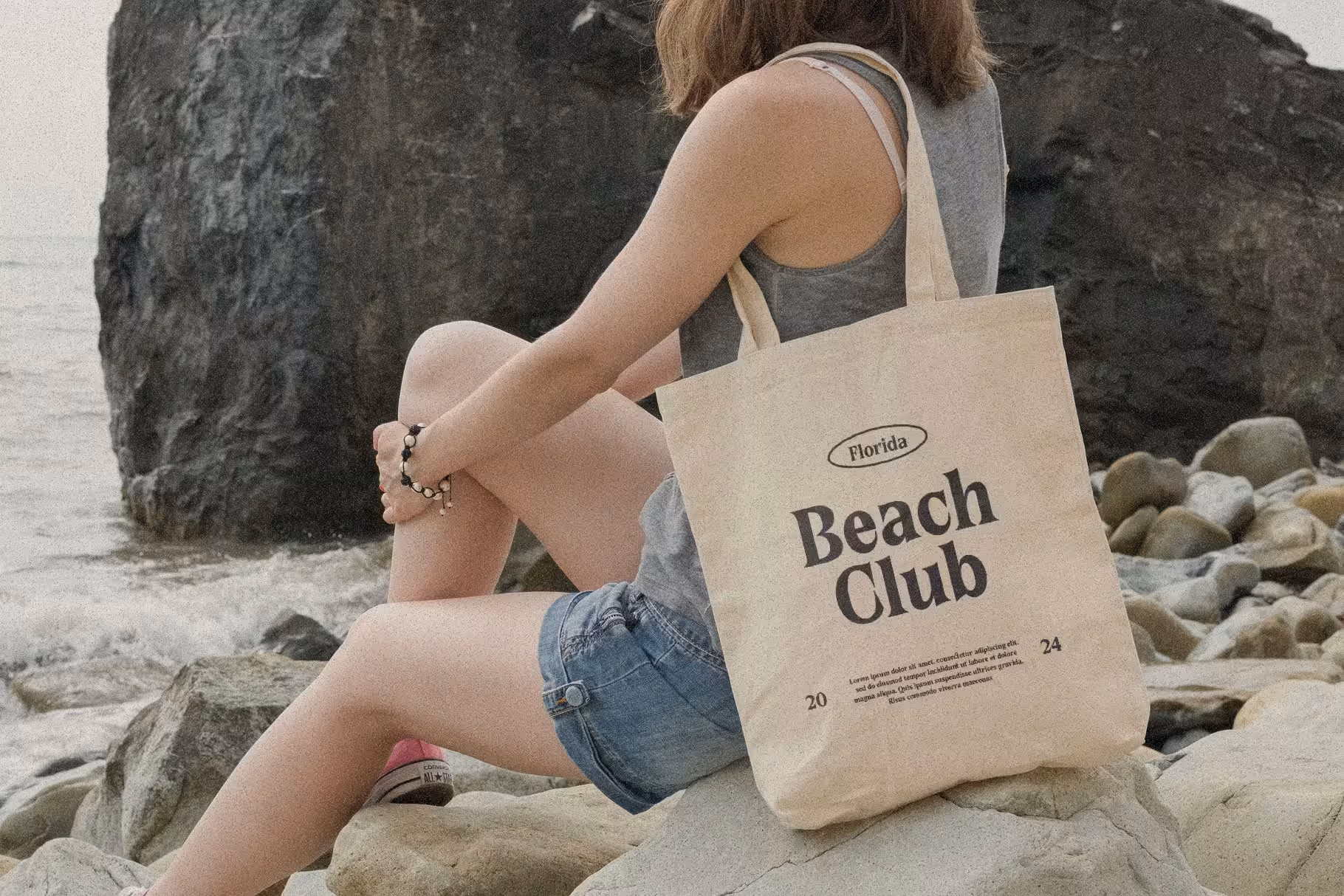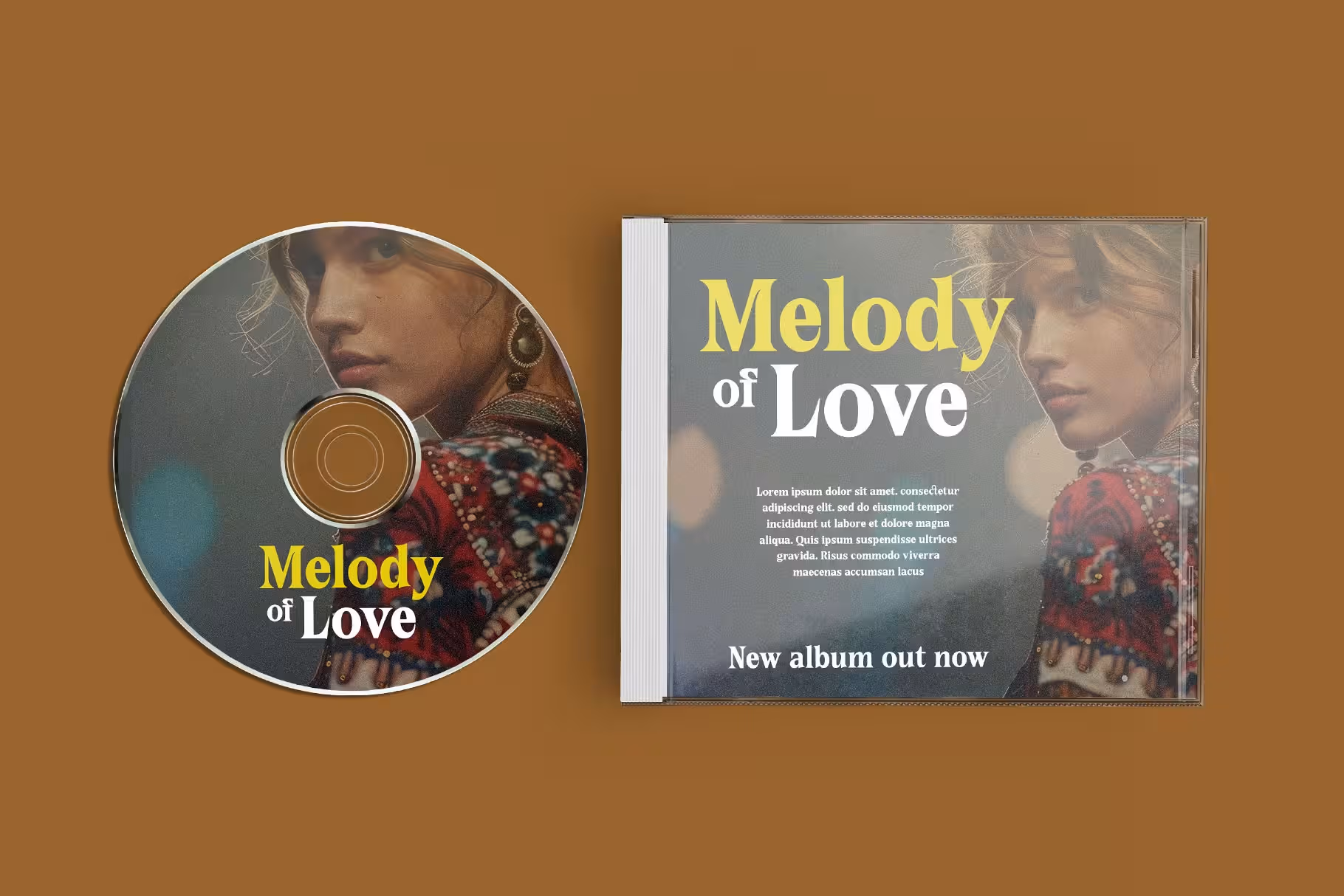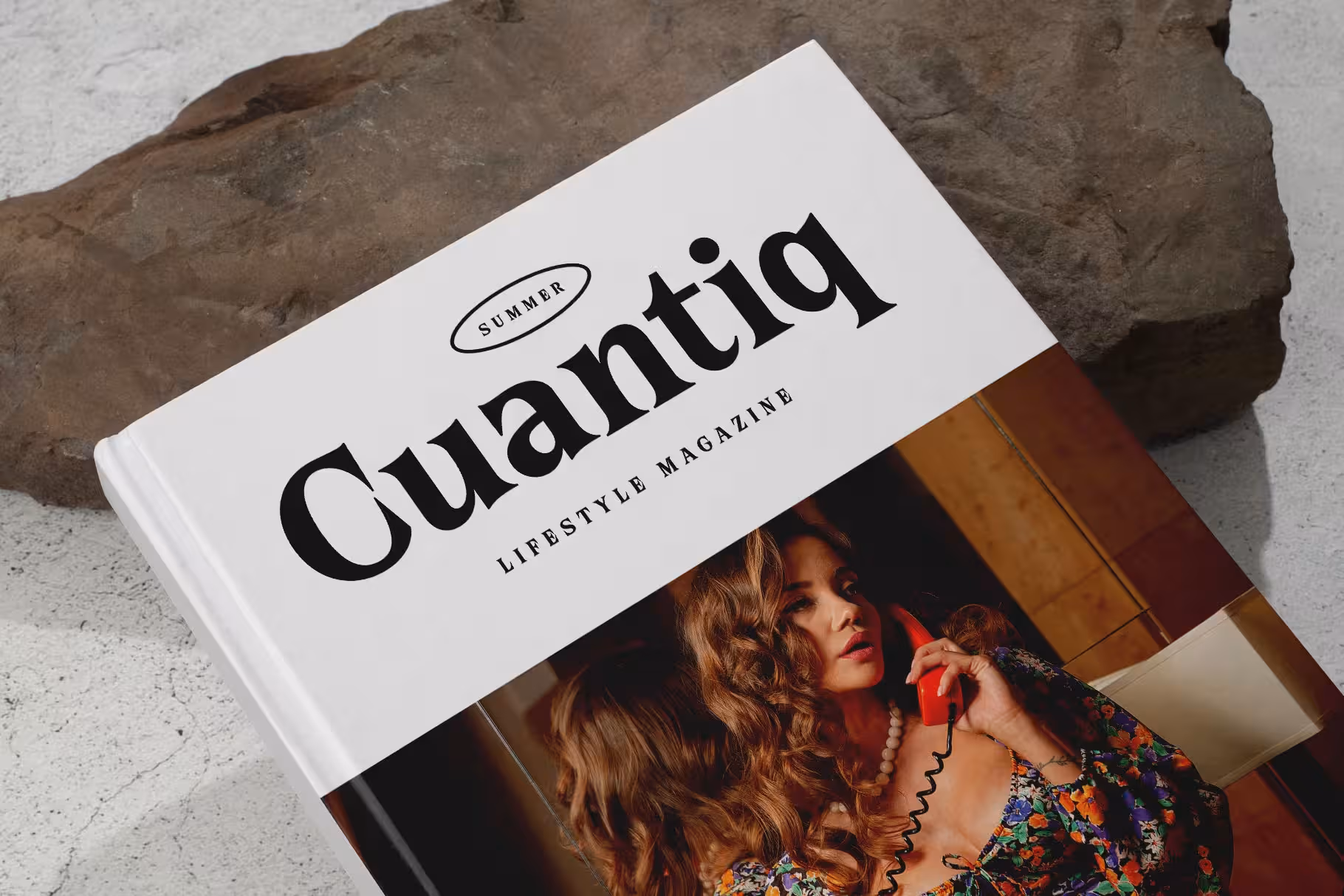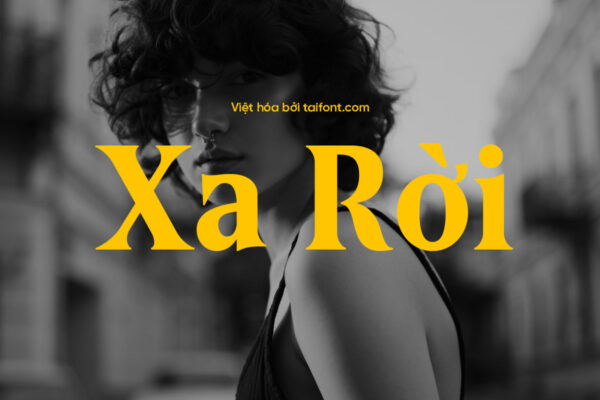
Giới thiệu về Font TF Gastey Việt hóa
TF Gastey Việt hóa là một font chữ có chân (serif) nổi bật với thiết kế đậm, mạnh mẽ và đầy cá tính, lý tưởng để tạo nên sự ấn tượng và phong thái đẳng cấp cho mọi thiết kế. Font này toát lên vẻ vững chãi, uy quyền và một chút nét cổ điển hiện đại, phù hợp để thu hút mọi ánh nhìn và khẳng định sự chuyên nghiệp.
Với đặc điểm là nét đậm, kích thước lớn và khả năng tạo ấn tượng thị giác mạnh mẽ, Gastey là lựa chọn hoàn hảo cho các ấn phẩm cần sự nổi bật và phong cách, đặc biệt là trong các lĩnh vực:
- Thiết kế thời trang: Hoàn hảo cho các thương hiệu thời trang cao cấp, từ logo, nhãn mác sản phẩm, đến các chiến dịch quảng bá bộ sưu tập. Font này giúp truyền tải vẻ đẹp thanh lịch, đẳng cấp và độc đáo của trang phục, nâng tầm giá trị thương hiệu.
- Thiết kế tạp chí: Lý tưởng để sử dụng cho các tiêu đề chính, lời dẫn, hoặc nội dung bài viết trong các tạp chí về thời trang, nghệ thuật, kiến trúc, hoặc lối sống. Nét chữ có chân đậm của Gastey giúp tăng tính trang trọng và dễ đọc, đồng thời tạo cảm giác cao cấp, thu hút độc giả.
- Thiết kế nhận diện thương hiệu: Phù hợp cho logo, tagline hoặc bộ nhận diện thương hiệu muốn truyền tải sự vững chắc, uy tín và sự sang trọng. Gastey giúp xây dựng một hình ảnh thương hiệu mạnh mẽ và dễ nhận diện.
Với TF Gastey Việt hóa, bạn có thể dễ dàng thổi hồn mạnh mẽ, sự tinh tế và vẻ đẹp hoàn hảo vào các thiết kế, tạo ra những sản phẩm không chỉ đẹp mắt mà còn đầy cảm xúc và sức hút đặc biệt.
Font Việt hóa TF Gastey